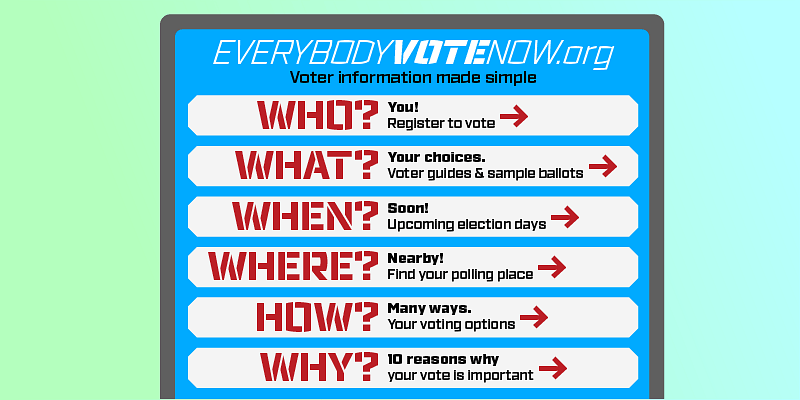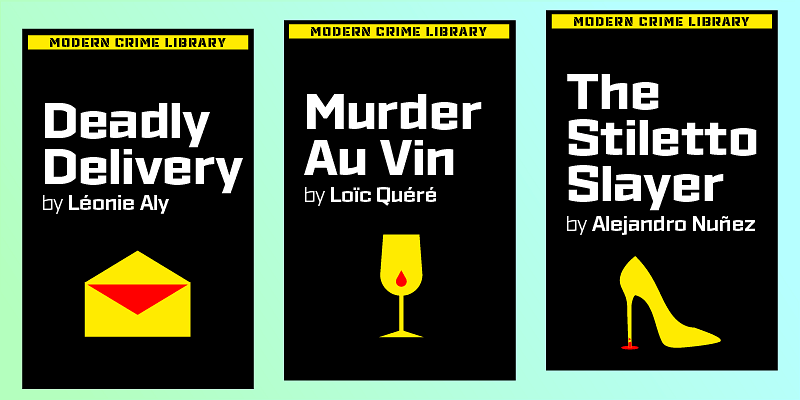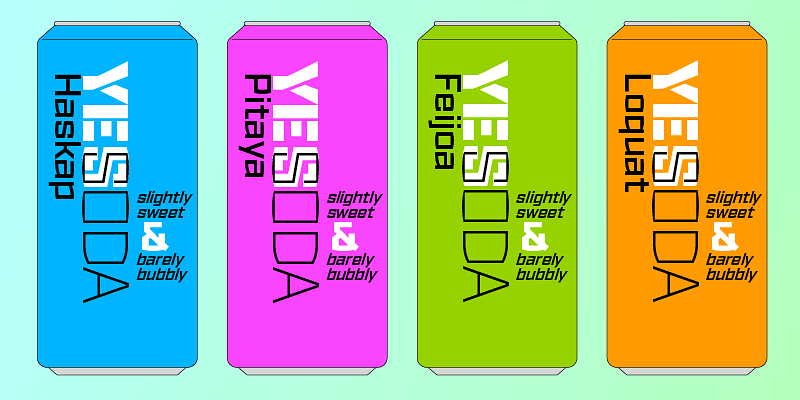
インダストリアルレターは、仕事、強さ、創意工夫を連想させます。その頑丈な文字は、職人技と素材の賜物であり、繊細なセリフやヘアラインストロークが消えてしまうような状況を乗り切る必要性から生まれたものです。ロシアの構成主義的なプロパガンダポスターに使われている文字も同様です。曲線が少なく、モジュール化されたフォルムのアルファベットは、機械とそれを使う労働者の新しい時代の到来を告げています。 「Ironstrike」は、インダストリアルレタリングと構成主義的レタリングに対するオマージュです。硬質な形状と背の高い小文字は、力強さとテクノロジーを連想させます。7 つのウェイトとそれに合わせたイタリック体のフォントが、困難なデザインに取り組む武器となります。細いライトウェイトはホワイトスペースを強調し、パワフルなヘビーウエイトは過激な見出しを盛り上げます。強烈な 17.5 度の傾斜のイタリックが、ページを横切りながらメッセージを強調します。OpenType の表形式の数字と任意の数を指定できる分数が数字を難なく処理します。14 のステンシルフォントには、それと組み合わせて使用できる幅広いディスプレイフォントが用意されています。130 以上の言語をサポートしているため、世界中の読者に対応できます。「Ironstrike」は、注目を集めるための戦術的なツールとして最適です。